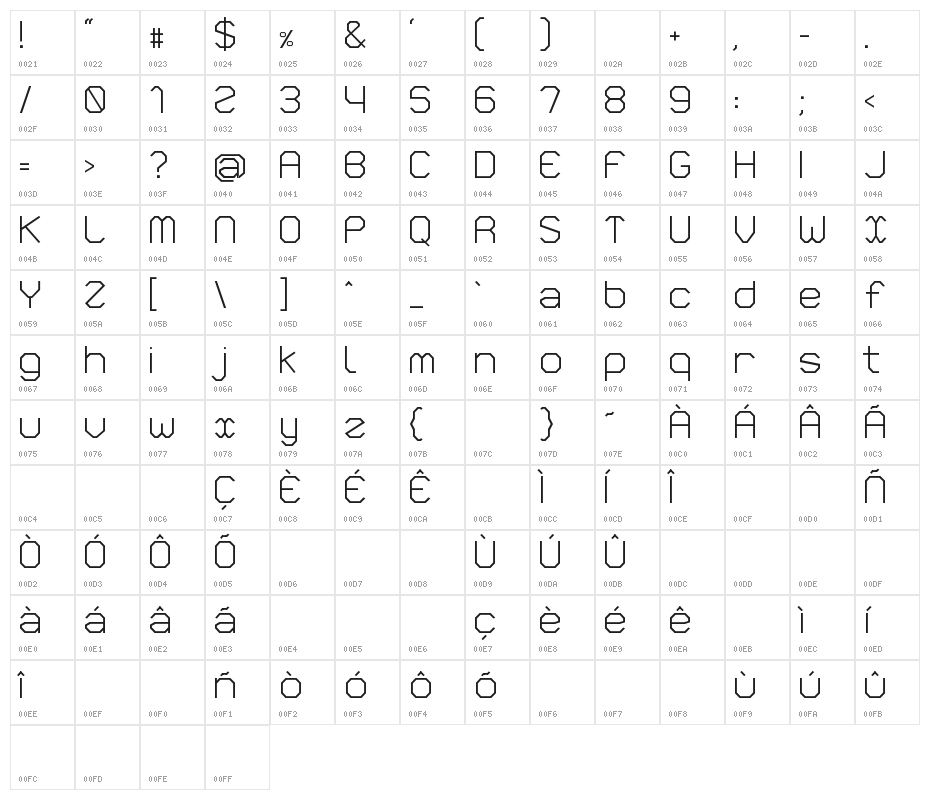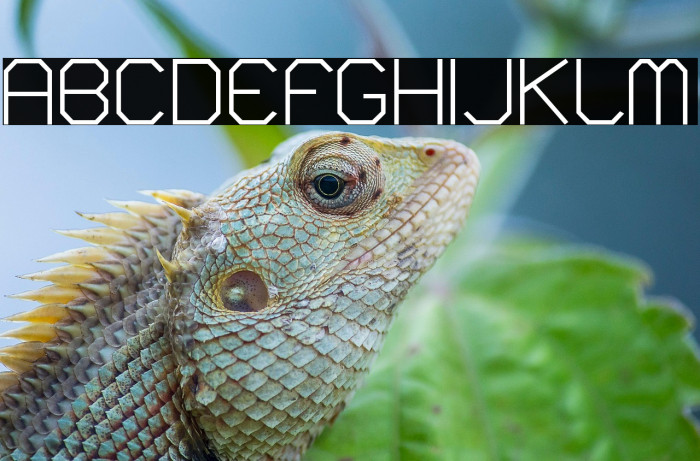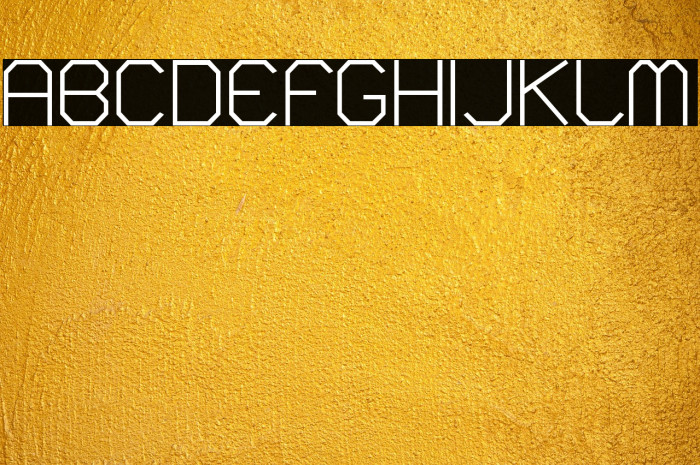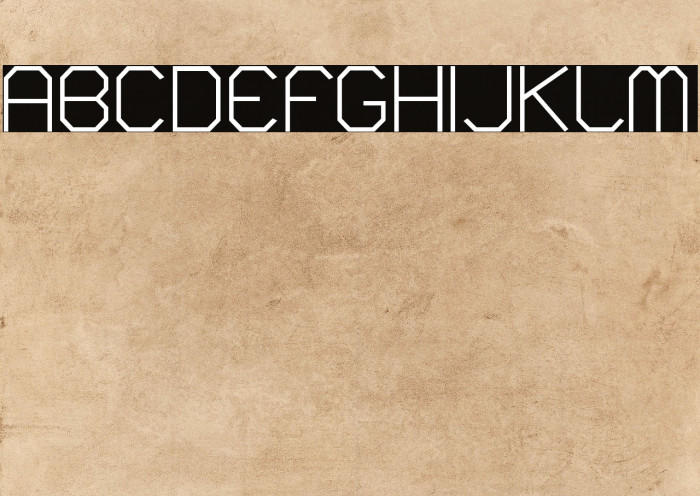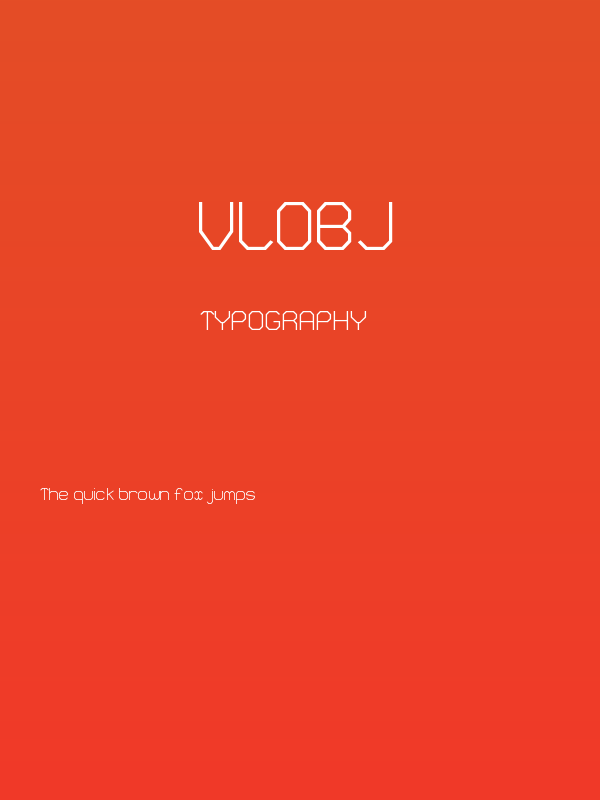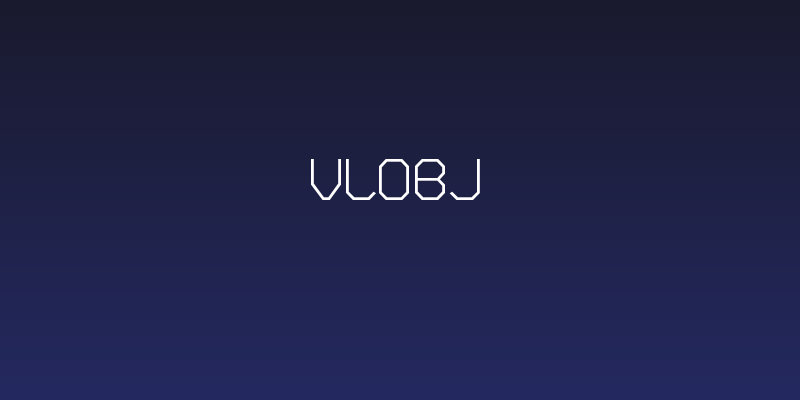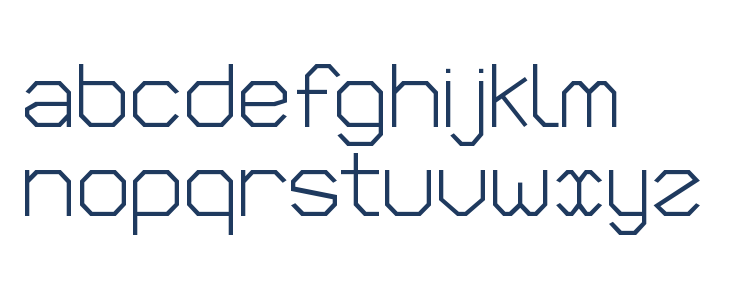
VLOBJ Font
✎ Futuristic
| Anwendungsfall | Logos, Headlines, Posters |
| Vorgeschlagene Projekte | Ideal for technology branding, sci-fi themed projects, video game interfaces, and modern poster designs. |